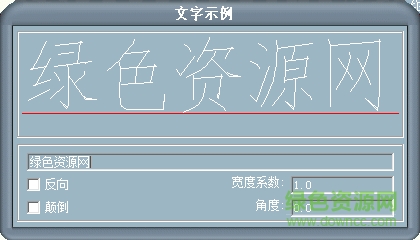
umhz.shx
umhz.shx字體是一款常用語cad制圖軟件中的重要字體,字體纖細使用簡單能有效顯示cad圖紙信息。快來綠色資源網(wǎng)下載體驗吧!
umhz.shx字體介紹
umhz.shx是autocad的字體文件,一般在查看圖紙的時候如果使用了umhz.shx字體而計算機中沒有它,則會無法正常顯示。